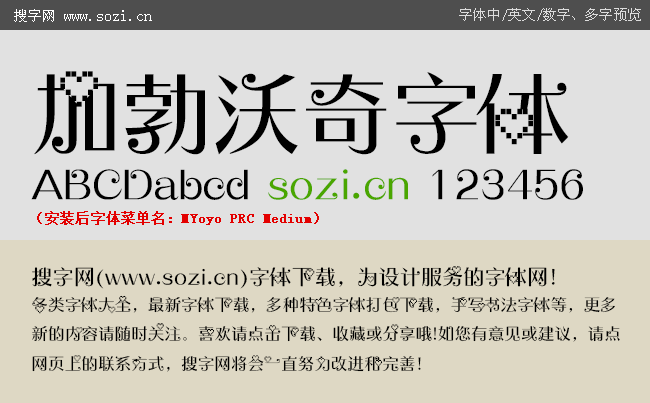
加勃沃奇字體
搜字網(wǎng)給大家提供一款很藝術(shù)的手機(jī)中文字體下載。名字叫加勃沃奇字體,這款手機(jī)字體是將宋體字進(jìn)行了藝術(shù)設(shè)計(jì),字體間又加上了漂亮的心形圖案,增添了趣味性,適合喜歡手機(jī)字體個(gè)性一些的朋友在手機(jī)上安裝使用。